Overtone y Set Snail, 2020
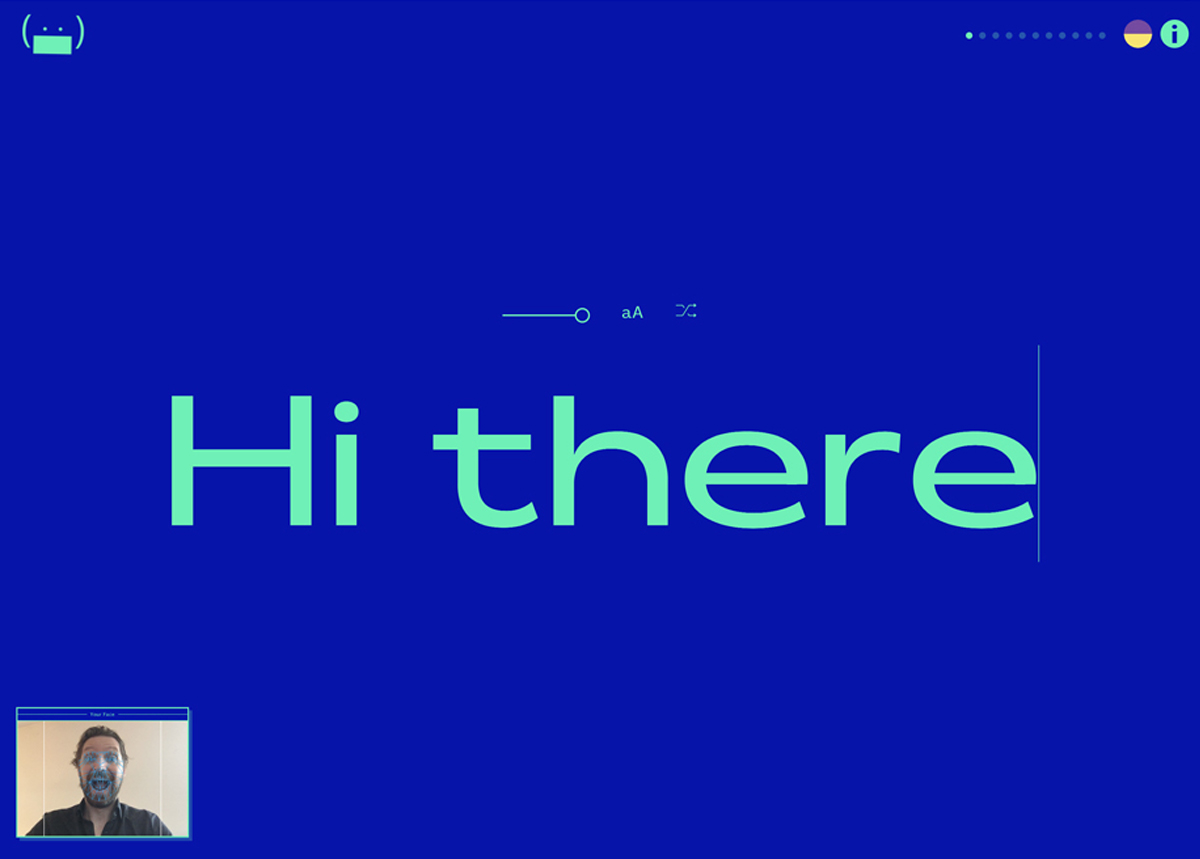
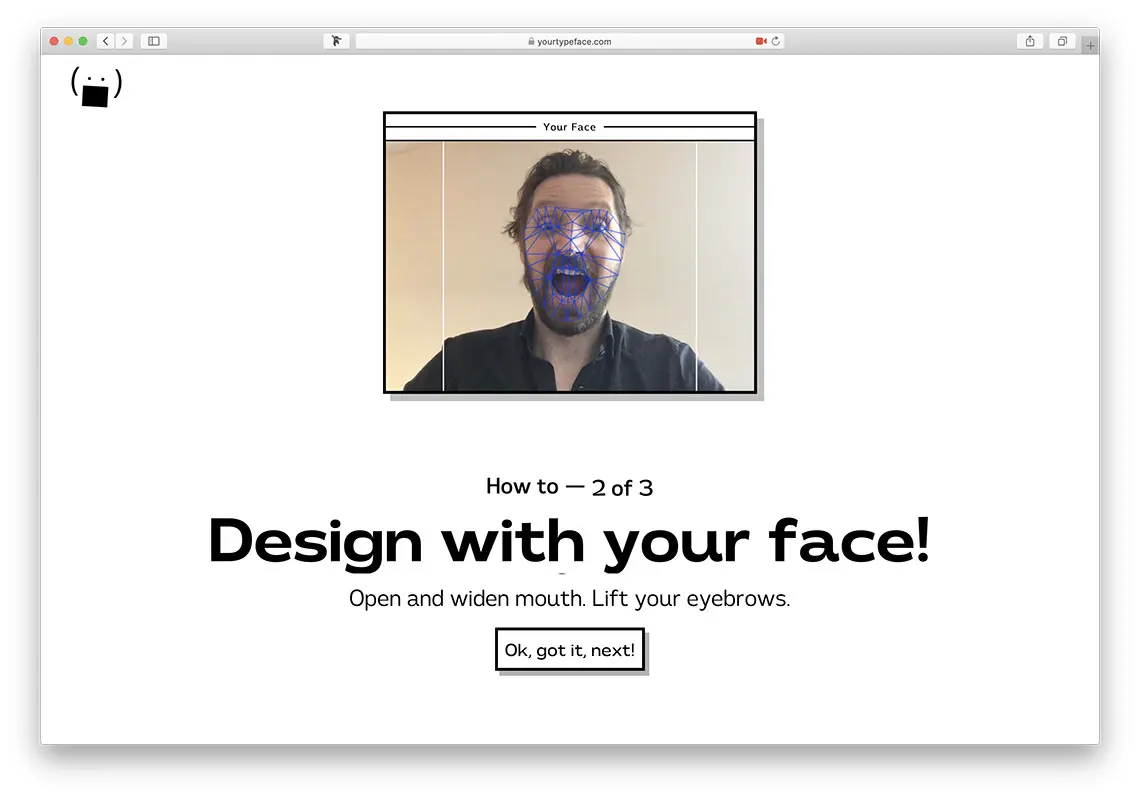
Relevancia
Face-a-Type es un sistema que utiliza la cara del usuario como una herramienta de diseño tipográfico. A través del reconocimiento facial, el sistema conecta las proporciones y las expresiones faciales (como sonreír o sorprenderse) con los ejes de una tipografía variable.
Su principal aportación es la creación de una experiencia lúdica y experimental que permite a cualquier usuario generar una fuente personal de forma automática. El proyecto materializa la conexión entre los datos biométricos y los ejes de una tipografía variable.
La relevancia para esta investigación reside en ser un ejemplo de cómo la biometría puede funcionar como una interfaz para la personalización y generación tipográfica.
Clasificación
- Década: Década de 2020
- Función: Sistema de diseño tipográfico
- Contexto: Producto digital, Investigación / Experimental
- Grado de interactividad: Interacción débil o reactiva
- Input multimodal: No
- Tipo de input: Gestual
- Tipo de output: Transformación morfológica
- Tecnología empleada: BRFv5 Face Tracking, Tipografía variable
- Alfanumérica: Sí
- Mantiene codificación textual: Sí